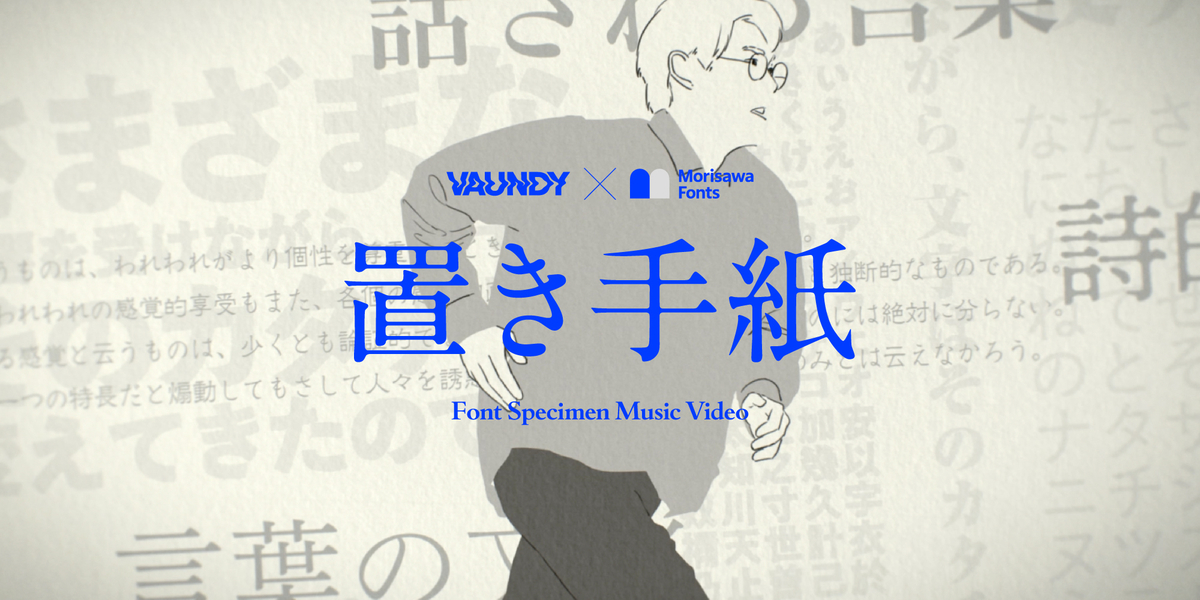
モリサワ Morisawa Fonts × Vaundy「置き手紙」 書き下ろし新曲にてコラボ実現、77書体で描かれた「フォントの見本帳」MV
モリサワは、クラウド型フォントサービス「Morisawa Fonts」とマルチアーティストVaundy氏とのコラボレーションにより、2022年11月28日(月)に配信された新曲「置き手紙」のミュージックビデオ(以下MV)を制作した。
MVの中で、2022年10月にサービスを開始した「Morisawa Fonts」で提供している77書体が歌詞を彩っており、「フォントの見本帳」をモチーフにした多様な演出が施されている。
フォントは、文字の「声」のような存在で、声の大きさやトーンで聞き手の受け取り方が変わるように、多くのデザインの中から場面にぴったりのフォントを選ぶことで伝えたいメッセージの印象を変えることができる。そのような、フォントが持つ魔法の力を実感できるきっかけになればと、今回のMVを制作したとのこと。
楽曲は、今回のために書き下ろされたVaundy氏の新曲となる。
映像制作は、カンヌ国際広告祭(カンヌライオンズ)などの受賞実績もあり、多数のMV演出実績を持つクリエイティブディレクター・川村真司氏がCCOを務めるワットエバー(以下Whatever)が担当。監督にはキャラクターデザインやイラストレーションから映像ディレクションまで総合的に手掛ける牧野惇氏を招聘。
フォントの見本帳(Font Specimen)を彷彿させるMVということで、Font Specimen Music Videoと謳い、これを解説する特設サイトも公開。
Vaundy氏、川村氏、牧野氏に制作の背景や見どころを対談形式で伺ったインタビューを掲載しているほか、MV内に登場するすべての歌詞を、使われているフォントで掲載している。
MVと合わせてご覧いただき、お気に入りのフレーズやフォントを見つけてみてみよう。
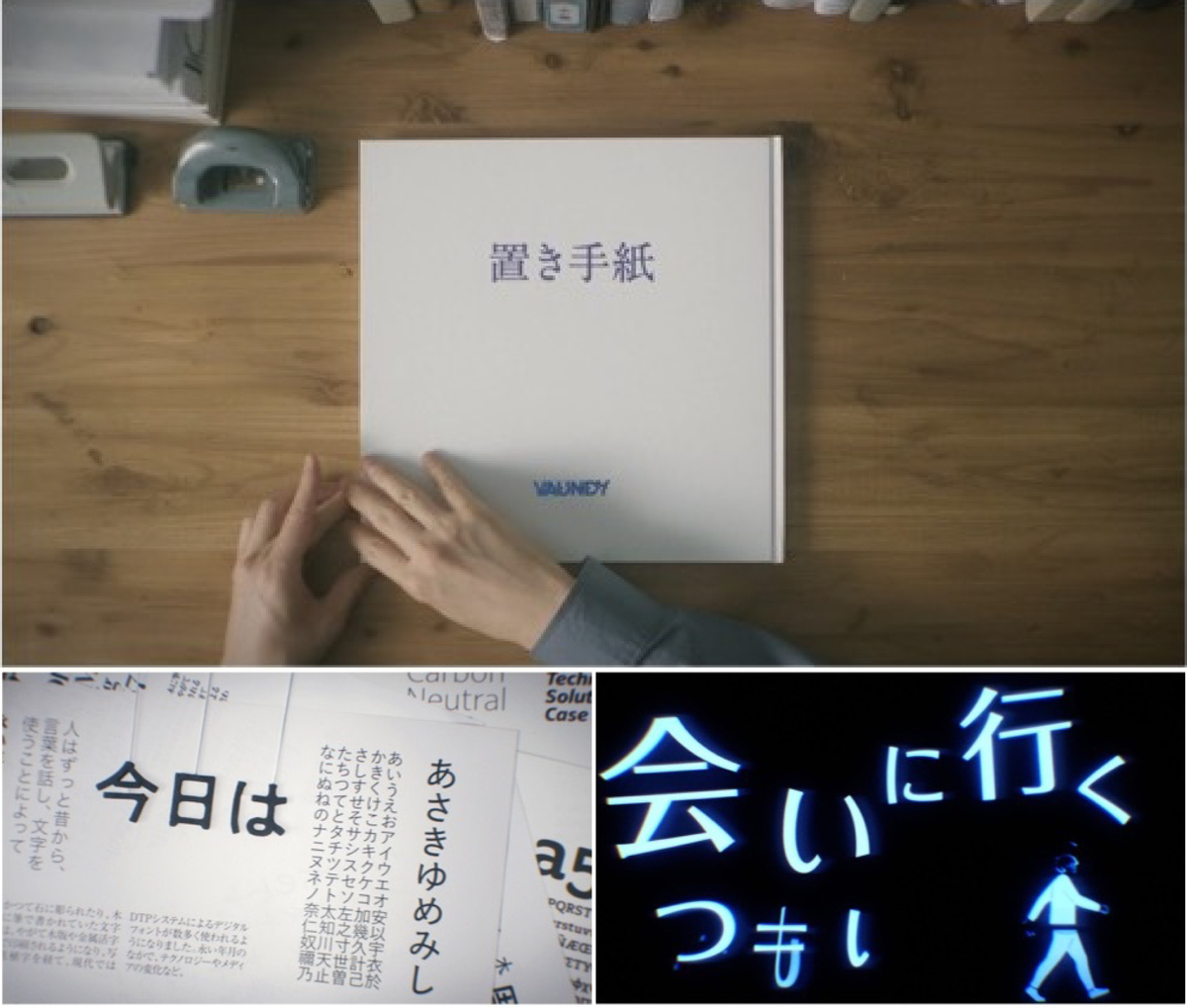
本作「置き手紙」は、Morsawa FontsとVaundyさんのコラボレーションから誕生したFont Specimen Music Videoとなる。
フォントは、伝えたい言葉に込められた想いを強めたり、時には変えてしまうような魔法の力を持っている。「置き手紙」という歌で繰り返される「魔法の言葉」を巡る物語を、フォントが溢れる世界観で映像化した。
Vaundy氏のパワフルな歌声と、それを可視化したさまざまなフォントたちの、書体見本帳を舞台にした共演を楽しもう。
▼マルチアーティスト・Vaundy氏のコメント
普段からモリサワのフォントを使っていたので、今回コラボが実現して感慨深いです。これまではあまり作ってこなかった、文字を見せるMVになるということを意識して、歌詞を書き上げました。ブラックライトを使った「クラフトモーション」のシーンが気に入っています。密度が濃い素晴らしいMVが完成しました。
▼クリエイティブディレクター・川村真司氏のコメント
まさに文字が主人公になっているMVになったと思います。文字が「膨らまされたり」「吹き飛ばされたり」することで感情を持って演じている様に見える表現ができました。Morisawa Fontsはクラウドでフルデジタル化した一方で、今回のMVはアナログにこだわったという、その対比が面白く、楽しんでいただけるのではと思います。
▼映像ディレクター・牧野惇氏のコメント
自分の得意とする「クラフト」を生かすために、新たに「クラフトモーション」という手法を編み出しました。歌詞を何度も読み返して表現に合う文字を選んで撮影しています。制作は想像以上に手間がかかり大変でしたが、その甲斐あって素晴らしいMVに仕上がりました。絵を使うことを意識的に減らしたことで、文字が絵になって見える作品になったと思います。